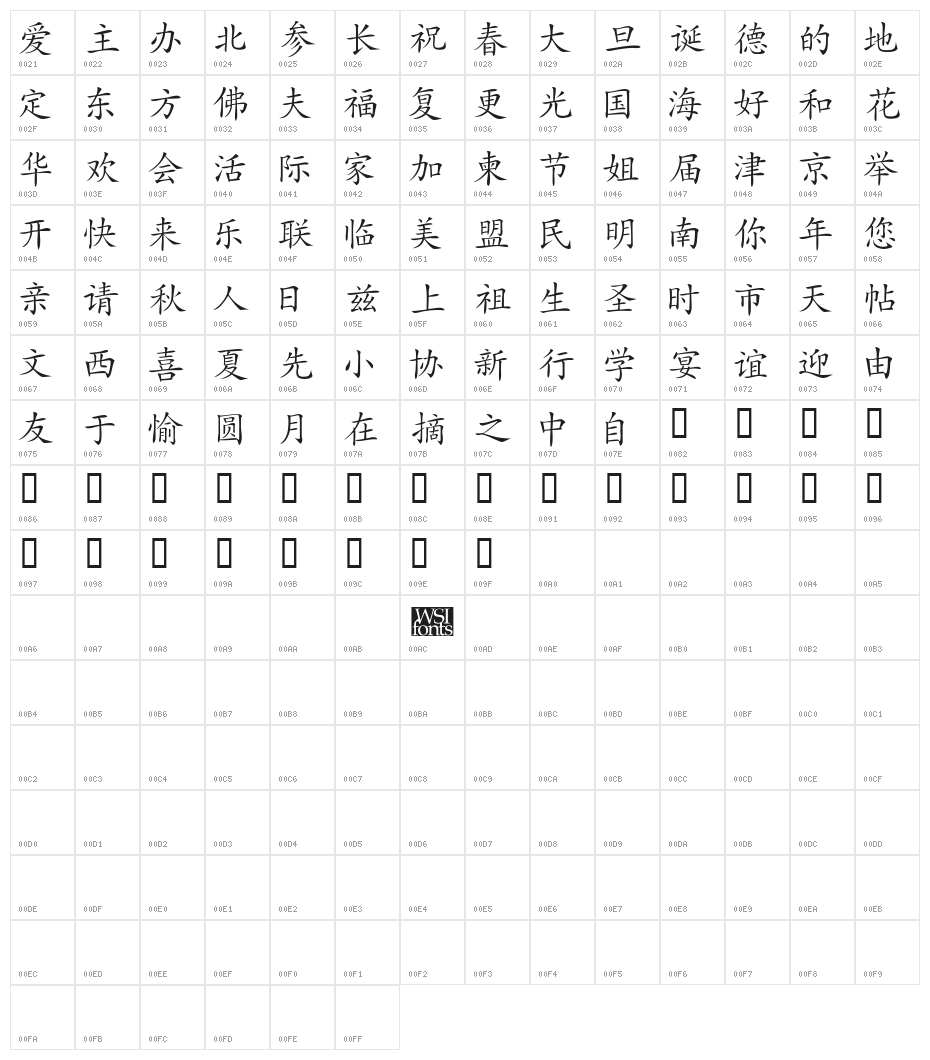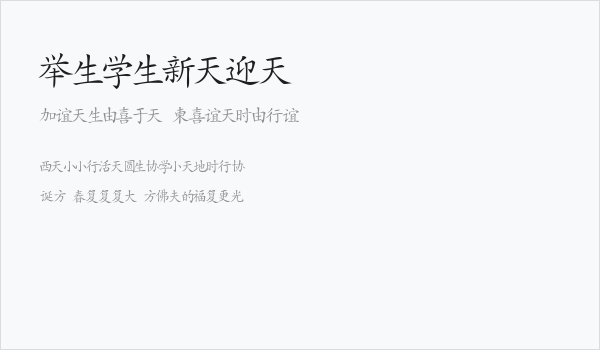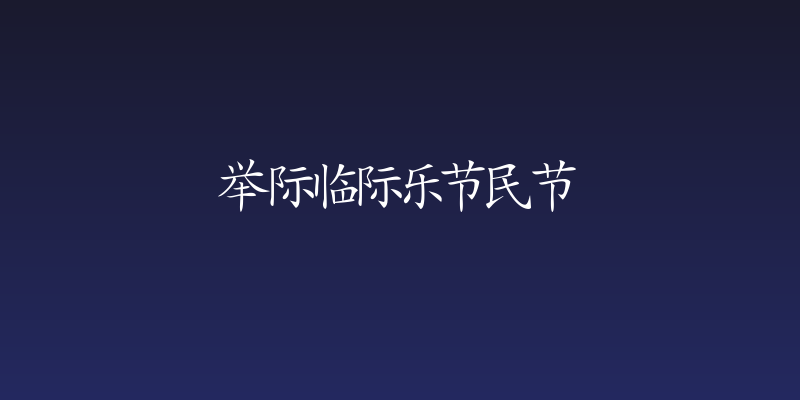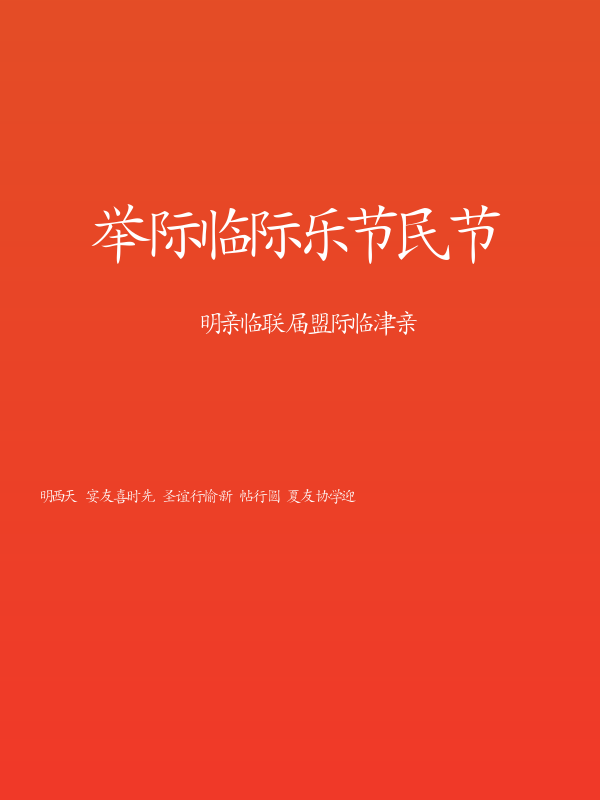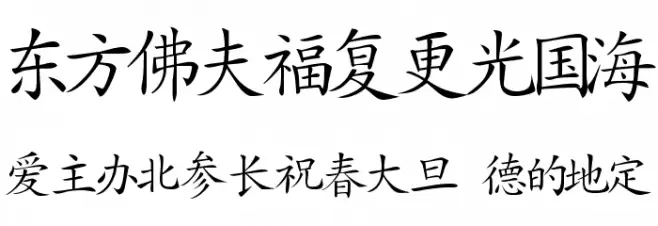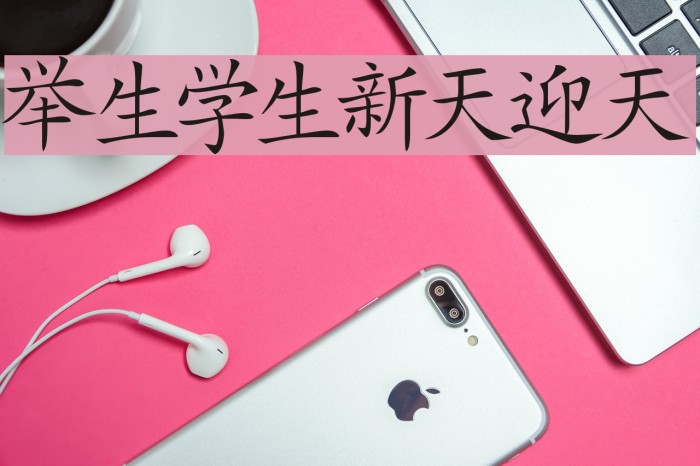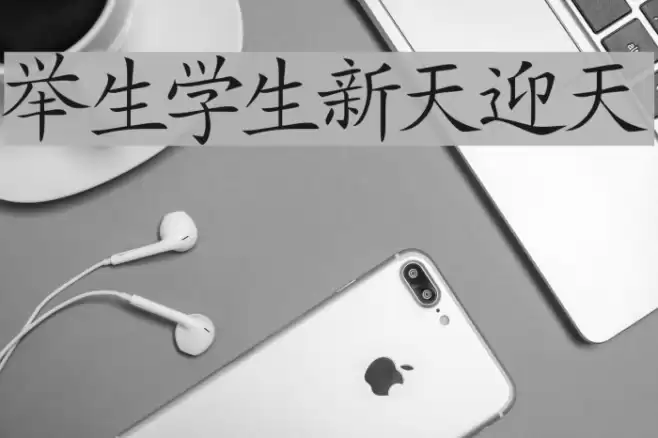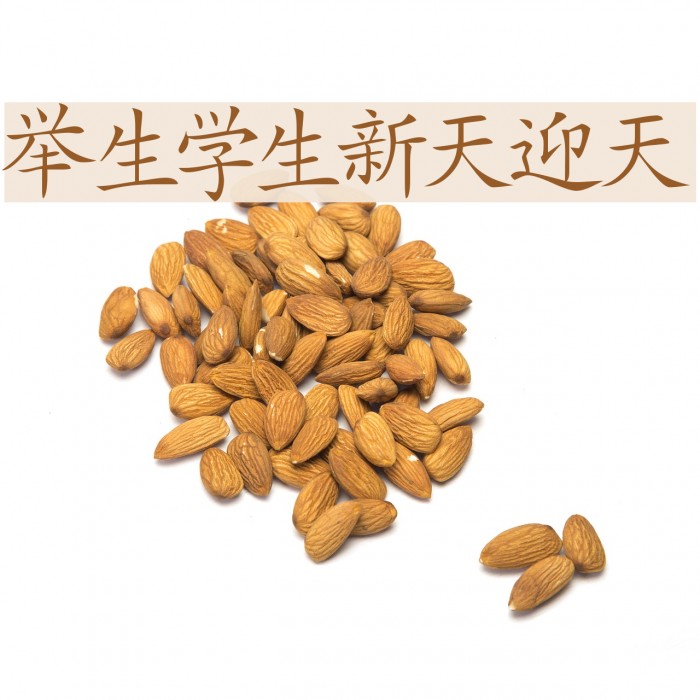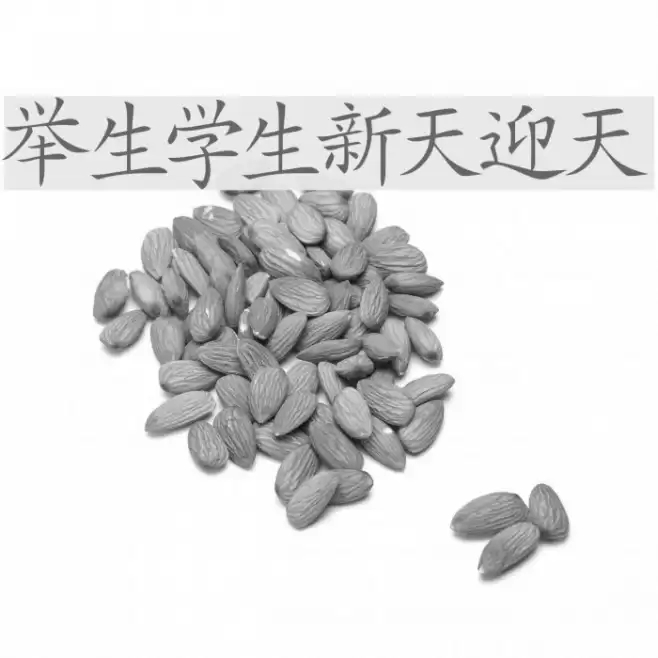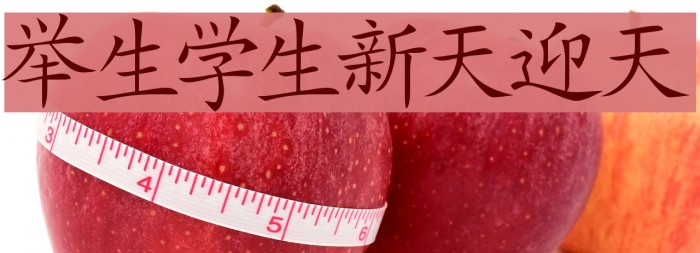
Japanese Font
| Stile generale | Traditional |
| Caso d'uso | Headlines, Artistic designs, Cultural projects |
| Progetti proposti | Ideal for cultural projects, traditional event invitations, artistic designs, and branding that requires an authentic Japanese aesthetic. |